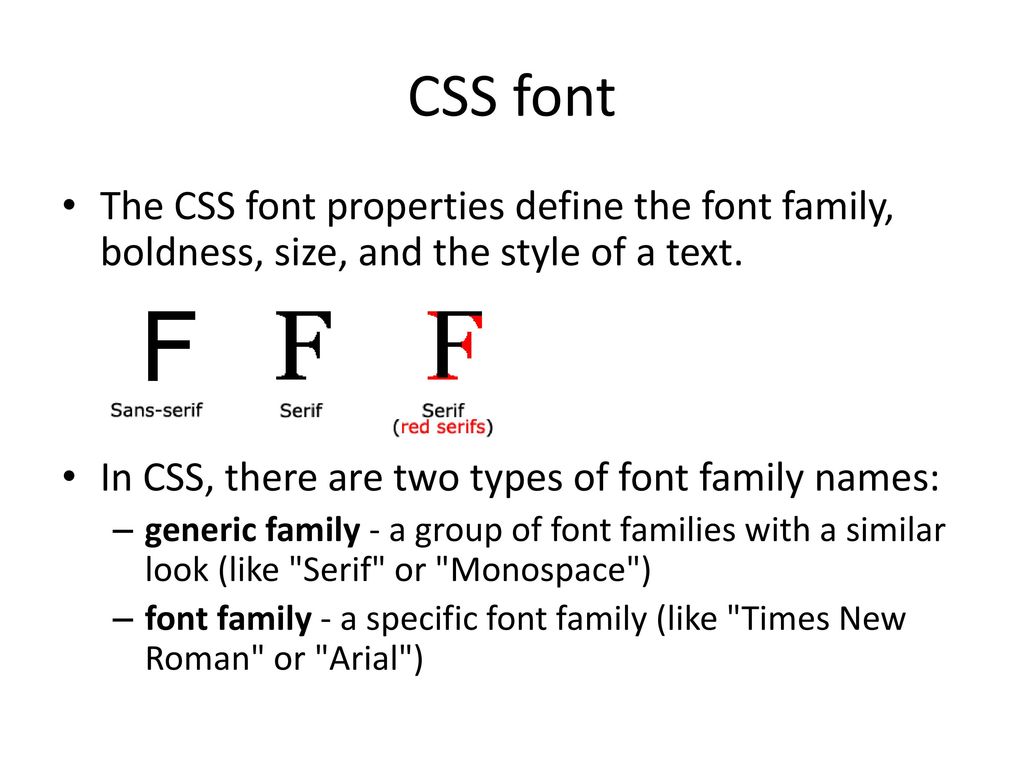
Fonts CSS HTML шрифты, цвет и размер текста
Свойства шрифта CSS определяют семейство шрифтов, смелость, размер и стиль текста.
Разница между засечками и шрифтами без засечек
Семейства шрифтов CSS
В CSS существует два типа имен семейств шрифтов:
- родовое семейство — группа семейств шрифтов с похожим видом (например, «засечка» или «однодисковая»)
- семейство шрифтов — конкретная семья шрифтов (например, «Times New Roman» или «Arial»)
| Generic family | Font family | Описание |
| Serif | Times New Roman Georgia | Шрифты с засечками имеют небольшие линии на концах на некоторых символах |
| Sans-serif | Arial Verdana | «Sans» означает без-эти шрифты не имеют линий на концах символов |
| Monospace | Courier New Lucida Console | Все одноместные символы имеют одинаковую ширину |
Примечание: На компьютерных экранах шрифты без засечек считаются более удобными для чтения, чем шрифты с засечками.
Семейство шрифтов
Семейство шрифтов текста задается с помощью свойства font-family.
Свойство font-family должно содержать несколько имен шрифтов в качестве «резервной» системы.
Если обозреватель не поддерживает первый шрифт, он пытается следующий шрифт и т. д.
Начните с нужного шрифта и заканчивайте родовым семейством, чтобы позволить обозревателю выбрать аналогичный шрифт в родовом семействе, если другие шрифты недоступны.
Примечание: Если имя семейства шрифтов больше одного слова, оно должно быть в кавычках, например: «Times New Roman».
В списке, разделенном запятыми, указано несколько семейств шрифтов:
Стиль шрифта
Свойство font-style в основном используется для указания текста курсивом.
Это свойство имеет три значения:
- normal — Текст отображается нормально
- italic — Текст показан курсивом
- oblique — Текст «опираясь» (косой очень похож на курсив, но менее поддерживается)
Размер шрифта
Свойство font-size задает размер текста.
Возможность управлять размером текста важна в веб-дизайне. Однако не следует использовать коррекции размера шрифта, чтобы сделать абзацы похожими на заголовки, или заголовки выглядят как абзацы.
Всегда используйте правильные HTML-теги, например < h2 >-< H6 > для заголовков и < p > для абзацев.
Значение размера шрифта может быть абсолютным или относительным размером.
Абсолютный размер:
- Устанавливает заданный размер текста
- Не позволяет пользователю изменять размер шрифта во всех браузерах (плохо для специальных возможностей)
- Абсолютный размер полезен, когда известен физический размер выходных данных
Относительный размер:
- Устанавливает размер относительно окружающих элементов
- Позволяет пользователю изменять размер текста в обозревателях
Примечание: Если размер шрифта не указан, по умолчанию для обычного текста, как и для абзацев, используется 16px (16px = 1em).
Задать размер шрифта с пикселями
Установка размера текста с пикселями дает полный контроль над размером текста:
Совет: При использовании пикселов можно по-прежнему использовать инструмент «Масштаб» для изменения размера всей страницы.
Установить размер шрифта с em
Чтобы разрешить пользователям изменять размер текста (в меню обозревателя), многие разработчики используют EM вместо пикселов.
Единица измерения размера em рекомендуется консорциумом W3C.
1em равен текущему размеру шрифта. Размер шрифта по умолчанию в обозревателях — 16px. Таким образом, по умолчанию размер 1em является 16px.
Размер можно вычислить от пикселов к EM использующ эту формулу: пикселы/16 =EM
В приведенном выше примере размер текста в EM совпадает с предыдущим примером в пикселях. Однако, с размером EM, можно настроить размер текста во всех браузерах.
К сожалению, есть еще проблема с более старыми версиями IE. Текст становится больше, чем он должен, когда сделал больше, и меньше, чем он должен, когда сделал меньше.
Используйте комбинацию процентов и EM
Решение, которое работает во всех браузерах, заключается в том, чтобы задать размер шрифта по умолчанию в процентах для элемента <BODY>:
Наш код теперь отлично работает! Он показывает тот же размер текста во всех браузерах, и позволяет всем браузерам, чтобы увеличить или изменить размер текста!
CSS sans-serif generic-family category
В отличие от serif, глифы в sans-serif имеют простые окончания штриха . Например, Lucida Sans, Open Sans, Arial, Lucida Sans Unicode, Helvetica, Trebuchet MS, Fira Sans включены в категорию общего семейства шрифтов без засечек.
Свойство семейства шрифтов
Семейство шрифтов без засечек.